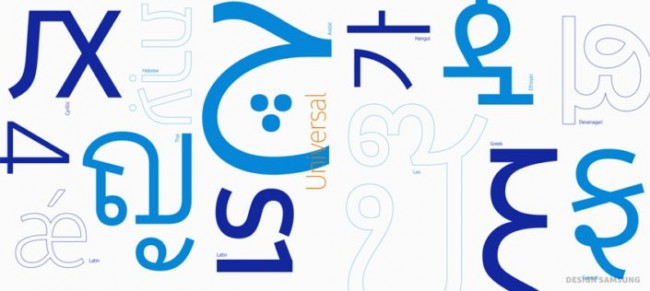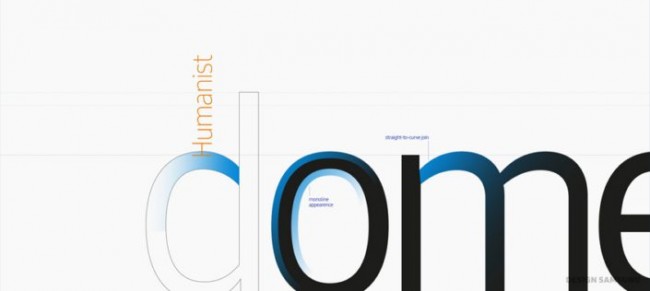
Tak wygląda SamsungOne. Nie, to nie smartfon. To nowy... font
Kiedy produkujesz smartfony, lodówki, pralki i telewizory, trudno jest utrzymać jeden konkretny styl urządzeń. Samsung chce ujednolicić swoją markę poprzez nowy font SamsungOne, który od teraz będzie zdobił wszystko, co związane z tą firmą.
SamsungOne - jeden font, by rządzić wszystkimi
Trudno zliczyć wszystkie obszary, w których porusza się Samsung. Według Wikipedii, Samsung działa w:
Nawet patrząc na „naszą” działkę nowych technologii, kategorii i rodzin produktów jest mnóstwo. Ot, choćby seria Galaxy opierająca się na Androidzie i równoległa seria Gear oparta na Tizenie.
Samsung ma nowy pomysł na ujednolicenie wszystkich pionów. Jest nim nowy font.
SamsungOne to nazwa nowego fontu, który będzie wykorzystywany we wszystkich produktach firmy. Jest to zupełnie nowy krój pisma, który obejmuje znaki znajdujące się w 400 różnych językach (!) i obejmuje aż 25 tys. pojedynczych glifów, na które składają się pojedyncze znaki oraz konkretne ich kombinacje.
Dzięki temu w każdym miejscu na świecie zobaczymy ten sam font, który będzie stosowany przy produktach Samsunga.
Proces powstawania nowego fontu przedstawia poniższy film, na którym główny projektant, Neville Brody, opowiada o swoich inspiracjach.
Nowy font raczej nie będzie zdobił logotypów
Trudno mi wyobrazić sobie sytuację, w której obecne logotypy (np. Galaxy) zostaną zastąpione literami pisanymi w nowym kroju pisma. Można oczekiwać, że SamsungOne pojawi się „dookoła” produktów - na pudełkach, w reklamach, czy w instrukcjach.
Font zobaczymy też na wyświetlaczach urządzeń, np. w menu. SamsungOne został zaprojektowany tak, by wyglądać dobrze zarówno na małym ekranie (np. smartwatcha), jak i na billboardzie.
Samsung idzie śladem Apple'a i Google'a
W świecie nowych technologii własnym fontem posługuje się także inne firmy, np. Apple oraz Google. W przypadku Apple przez długi czas naczelnym fontem była Helvetica i Helvetica Neue, ale obecnie zastępuje je font San Francisco. Widać go nie tylko w interfejsie (pierwszy raz pojawił się w Apple Watch, a obecnie jest fontem w OS X i iOS), ale także w sprzęcie (San Francisco został wykorzystany w literach klawiatury MacBooka 12).
W przypadku Google naczelnym fontem jest Roboto, który od 2013 roku pojawia się w kolejnych produktach Google’a. Jest to domyślny krój w Androidzie, ale Roboto znajdziemy też w wielu usługach, np. Google+, Google Play, YouTube, czy Mapach Google.
Z kolei w świecie foto bardzo charakterystycznym fontem jest ten stosowany przez firmę Leica. Smartfon Huawei P9, który powstał we współpracy z Leicą, wykorzystuje ten font w aplikacji aparatu, a także w opisie obiektywu na obudowie.
Konkretny, konsekwentnie stosowany font, jest bardzo ważnym elementem w budowaniu marki w świadomości klientów. Na co dzień większość z nas nie zwraca na to uwagi, ale podświadomie rejestrujemy takie drobnostki. Kto z nas nie kojarzy charakterystycznego napisu „iPhone” napisanego czarnymi literami na białym tle?
Osobiście bardzo lubię, kiedy firma potrafi z dużą konsekwencją trzymać się takich - wydawałoby się - drobnostek. SamsungOne jest naprawdę dobrym posunięciem.